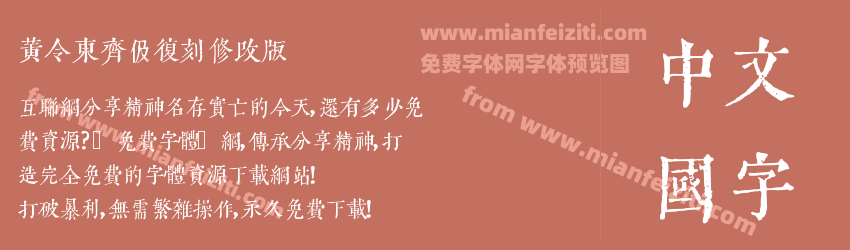
一款充满了古典气质的,可媲美康熙字典体的字体,深受大家喜爱。但是之前的版本有两个小问题,一是之前的版本没有英文和数字的字符。二是字体名称在PS中显示是英文的QIJIC。
而热心的站长修正了这两个问题,在原来的版本中加入了风格相似Oradano-Mincho数字英文 ,并把名称修改成了黄令东齐伋复刻以方便大家使用这款字体。
本款“黄令东齐伋复刻修改版”是一款书写很新颖的字体,字体大方,适合各种设计作品使用!欢迎下载!